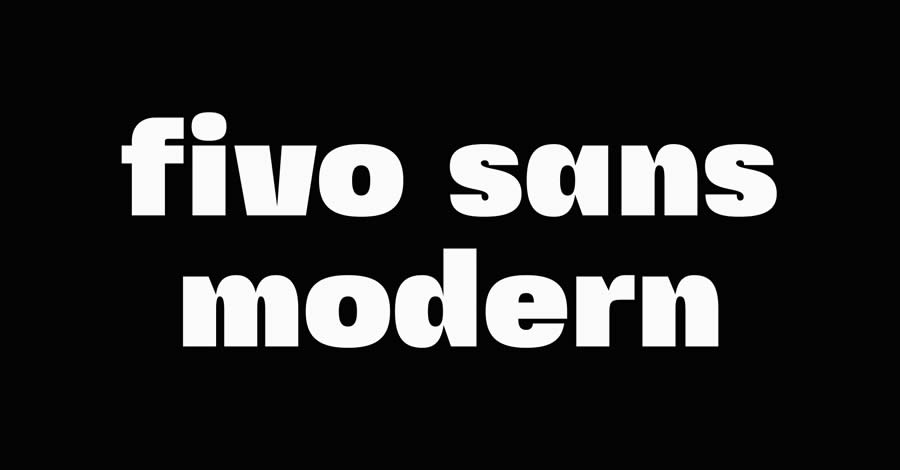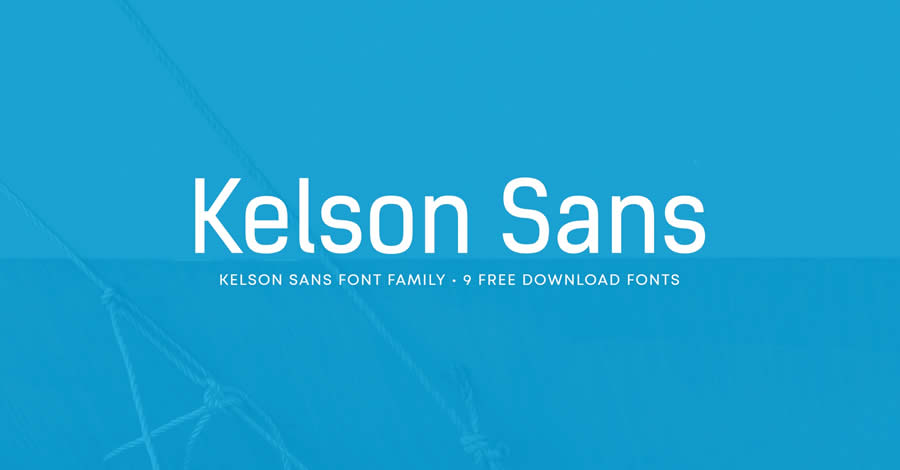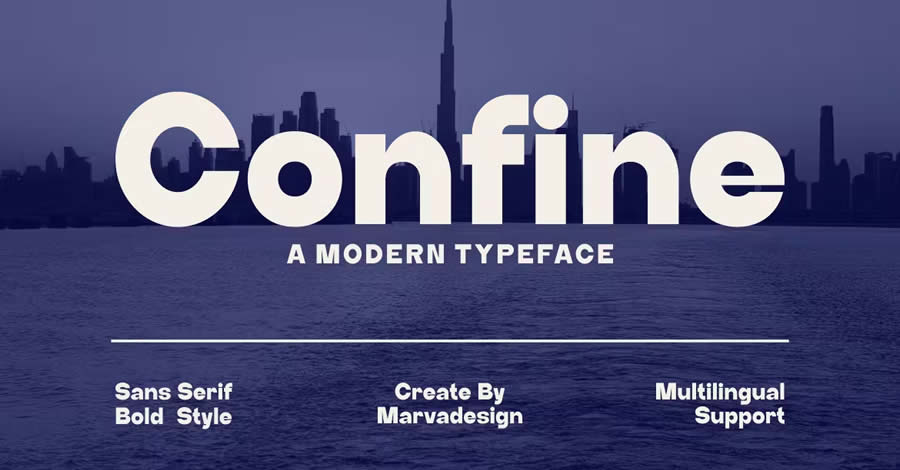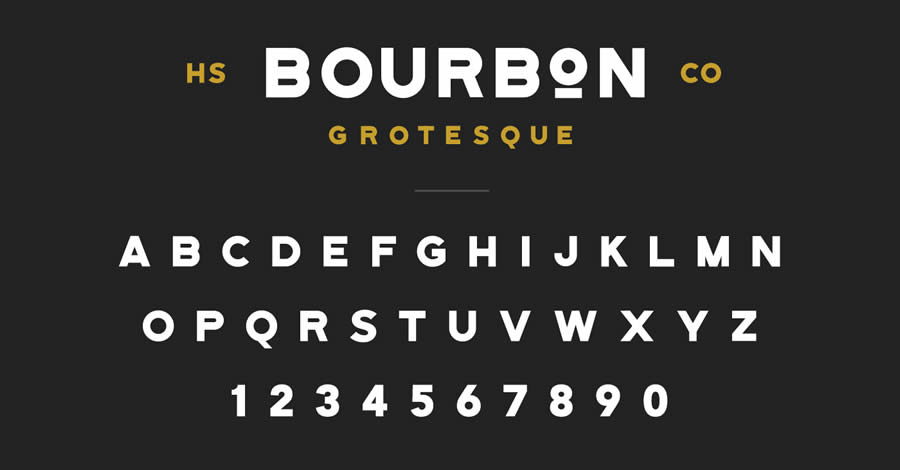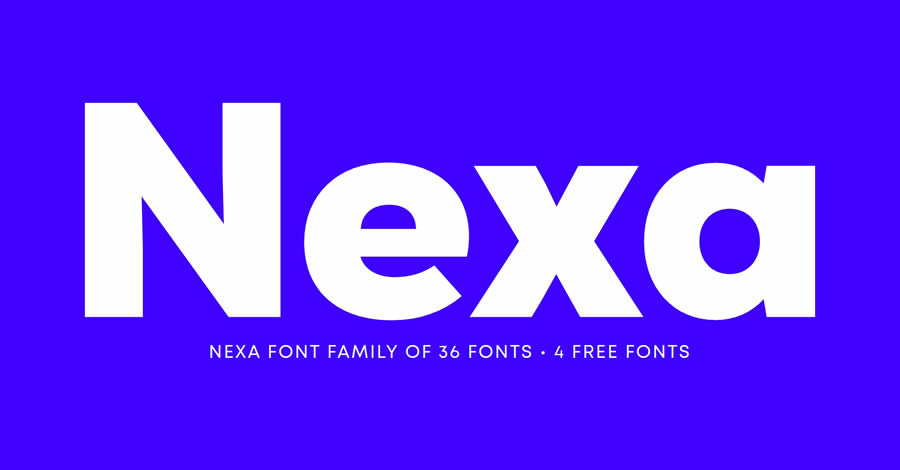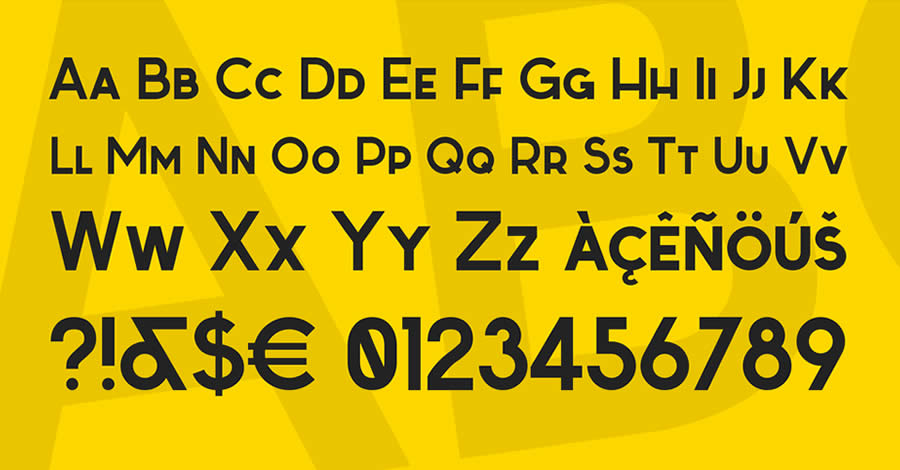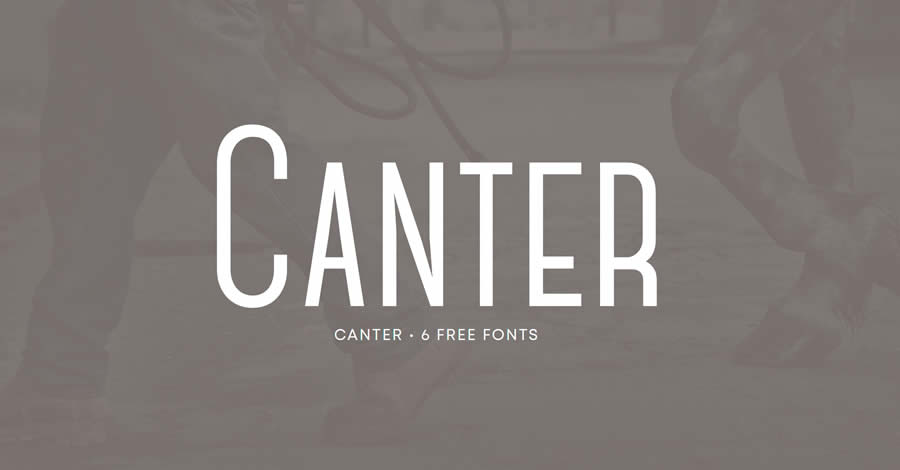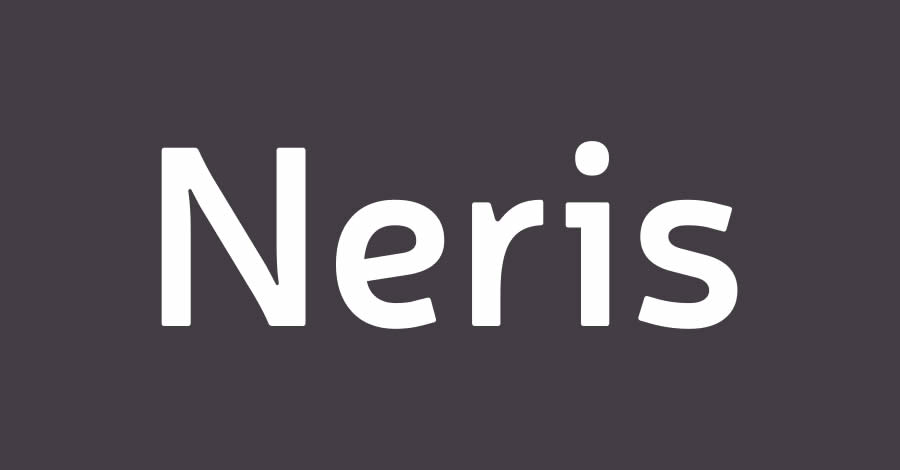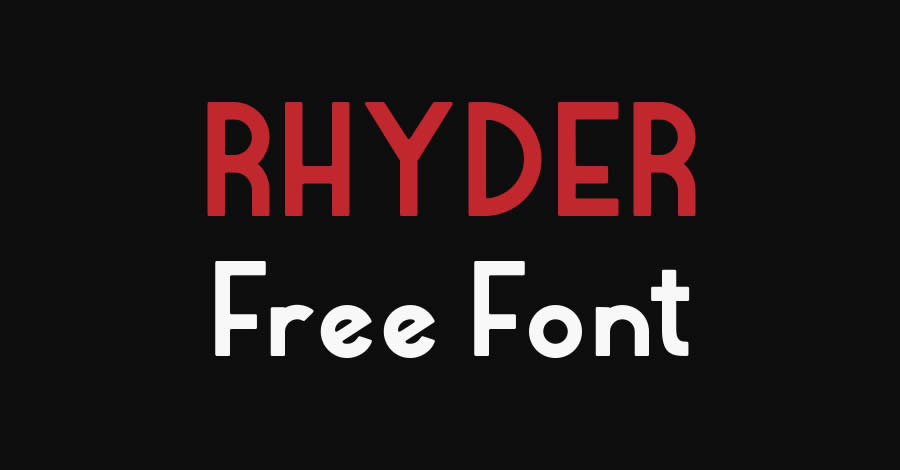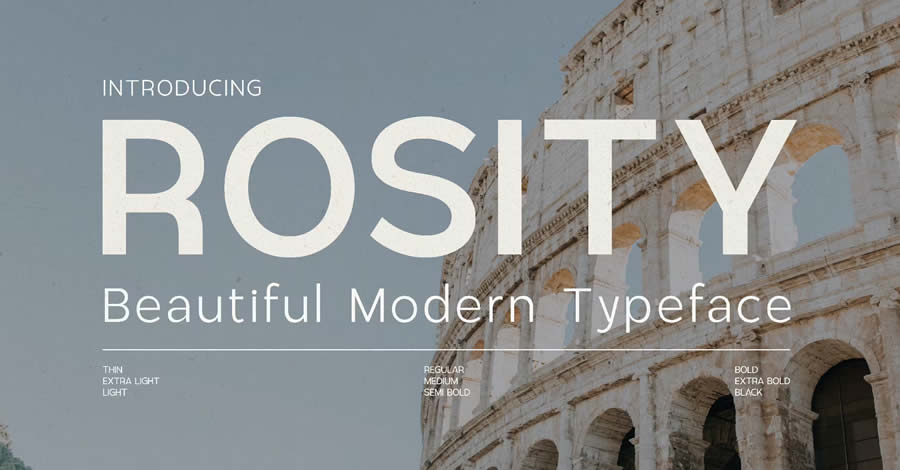
40+ Best Free Sans-Serif Fonts für Designer
Die Auswahl der Schriftart dreht sich darum, den richtigen Ton zu setzen, eine Botschaft zu vermitteln und Aufmerksamkeit zu erregen. Unter den verschiedenen Arten von Schriftarten haben sich Serifenlose einen besonderen Platz unter Designern erobert. Die Einfachheit von serifenlosen Schriftarten verleiht ihnen ein modernes und aufgeräumtes Gefühl, was sie zur bevorzugten Wahl vieler Kreativer macht, die ein zeitgemäßes Design erstellen möchten.
In dieser Sammlung teilen wir die besten kostenlosen serifenlosen Schriftarten. Es ist eine wahre Schatzkammer für diejenigen, die nach Schriftarten suchen, die ästhetischen Reiz mit Funktionalität kombinieren. Von schlanken und minimalistischen bis hin zu kräftigen und wirkungsvollen Schriftarten ist die Bandbreite der serifenlosen Schrift erstaunlich vielfältig.
Sie werden Schriftarten finden, die sich perfekt für Überschriften eignen, die Aufmerksamkeit erfordern, für Fließtexte, die gut lesbar sein müssen, oder für UI-Designs, die einen bestimmten Stil benötigen. Diese Schriftarten sind nicht nur schön; sie sind auch vielseitig einsetzbar und können sich verschiedenen Designkontexten anpassen, von Print bis Digital.
Für Freiberufler, Hobbyisten oder erfahrene Profis zielt diese Sammlung darauf ab, serifenlose Schriftarten bereitzustellen, die jedes Designprojekt aufwerten können. Egal, ob Sie ein Logo, eine Website, eine mobile App, eine Präsentation oder einen Social-Media-Beitrag entwerfen, die richtige Schriftart kann den Unterschied ausmachen. Tauchen wir also ein in die Welt der kostenlosen serifenlosen Schriftarten und entdecken einige versteckte Schätze.
Was sind Serifenlose Schriftarten?
Serifenlose Schriftarten sind für ihr elegantes und präzises Erscheinungsbild bekannt. Das Hauptmerkmal, das sie von Serifenschriften unterscheidet, ist das Fehlen kleiner Linien oder Striche an den Enden der Buchstaben, sogenannter „Serifen“.
Diese fehlende Verzierung verleiht serifenlosen Schriftarten ein einfaches und sauberes Erscheinungsbild. Sie zeichnen sich durch einheitliche Strichstärke in den Buchstaben aus, was sie sehr gut lesbar macht.
Diese Klarheit ist besonders vorteilhaft in digitalen Medien, wo Lesbarkeit auf Bildschirmen entscheidend ist. Designer bevorzugen serifenlose Schriftarten oft wegen ihrer Vielseitigkeit und modernen Anmutung.
Sie eignen sich hervorragend, um in verschiedenen Designprojekten, von Websites und Logos bis hin zu Druckmaterialien, ein wirkungsvolles und aufgeräumtes Erscheinungsbild zu schaffen. Ihre Einfachheit ermöglicht eine einfache Kombination mit anderen Schriftstilen und macht serifenlose Schriftarten zu einer flexiblen Wahl für verschiedene Designanforderungen.
Der Unterschied zwischen Serifen- und serifenlosen Schriftarten
Die Top kostenlosen serifenlosen Schriftarten für Kreative
Fivo Sans Modern Display Font Family (Kostenlos)
Fivo ist eine zeitgenössische Schriftfamilie, die Ihre Designs subtil aufwertet. Sie ist in verschiedenen Gewichtungen von fett bis extra schwarz erhältlich und verbessert die Typografie leise.
Confine Sans-Serif Typeface
Confine ist eine kühne serifenlose Schrift mit kräftigen und markanten Zeichen. Treten Sie aus dem Gewöhnlichen heraus und umarmen Sie die Stärke von Confine in Ihrem nächsten Markendesignprojekt.
Kelson Sans Font (Kostenlos)
Die Kelson-Familie bietet neun kostenlose Schriftarten mit Ziffern, Interpunktion und mehrsprachiger Unterstützung, damit Sie sie wirklich in verschiedenen Projekten verwenden können. Perfekt für lesbaren Webtext und Überschriften.
Bourbon Grotesque Font (Kostenlos)
Bourbon Grotesque vereint einen Retro-Touch mit einer Prise Modernität. Als kostenlose, komplett in Großbuchstaben geschriebene Schrift verleiht ihr charmanter Vintage-Stil Marken und Logodesigns eine zeitlose Ästhetik, die fasziniert und bestehen bleibt.
Rosity Modern Sans-Serif Typeface
Rosity ist eine serifenlose Schrift, die klare und prägnante Linien mit einer Prise Raffinesse verbindet. Maßgeschneidert für zeitgenössisches Design verleiht es Ihrer Typografie eine unausgesprochene Eleganz und sorgt dafür, dass jedes gelesene Wort einen subtilen, modernen Charme hat.
Airone verleiht jedem Design einen unbestreitbaren Punch und bietet eine kostenlose, extra fette serifenlose Schriftart, die Aufmerksamkeit erregt. Besonders geeignet für Titel und Überschriften unterstreicht sie eine starke, wirkungsvolle Präsenz und stellt sicher, dass Ihr Text nicht nur lesbar, sondern auch unvergesslich durchschlagend ist.